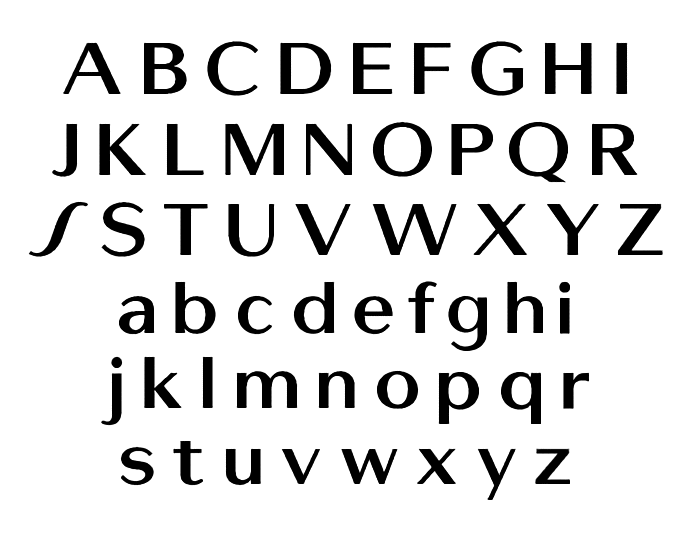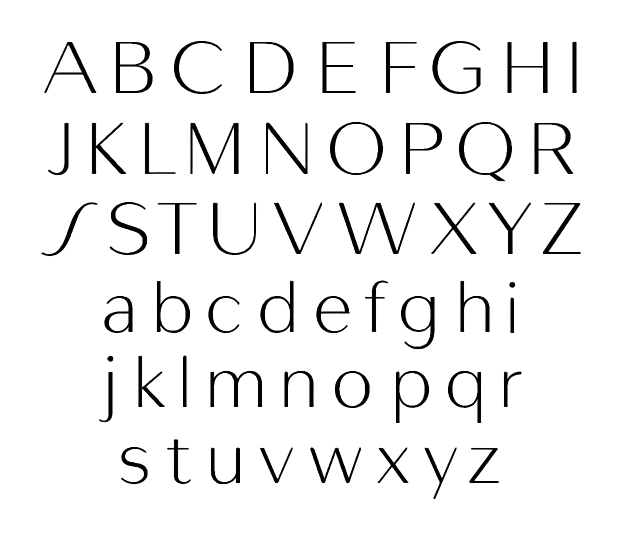
Shiseido
Adrian Frutiger Typefaces: The Complete Works, 2009
美しい資生堂のロゴタイプ。 資生堂ロゴの変遷で確認できるように、何度もモデファイされた。 現在のロゴで使用されているフォントは、クリエイティヴ・ディレクターであった安原和夫氏のもと、スイスの巨匠タイポグラファー、アドリアン・フルティガーによってデザインされた。 『Adrian Frutiger Typefaces: The Complete Works』によると、ベースはカッサンドルの Peignot のようである。 フォントは CastleType 社によってデジタル化された。 斜め掛かった S の形状はアールデコ期のフォントでよく見られる。